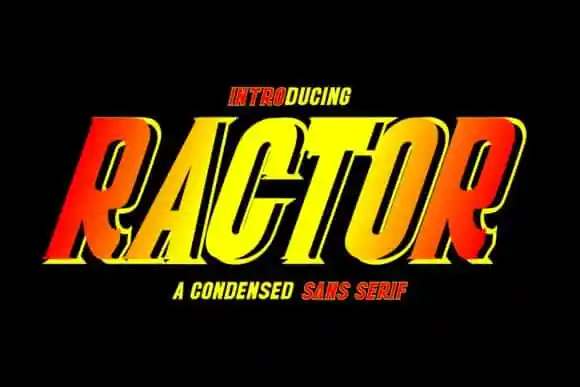
Ractor Display Font – Download Grátis
A Ractor Display Font é uma escolha perfeita para aqueles que procuram um tipo de exibição sem serif vintage e elegante. Conhecida por seu designer Teguh Pranata, a fonte oferece versões Regular e Outline. Ela destaca-se com seus caracteres redondos e prolongados, características que permitem uma aplicação perfeita em logotipos, branding e design de embalagens, entre muitos outros usos visuais. Esta tipografia cuidadosamente criada para fins de exibição é um verdadeiro must-have. Com seu estilo robusto e sofisticado, a Ractor será uma escolha brilhante para seus projetos digitais. Não perca esta oportunidade única de adicionar profundidade ao design de suas aplicações visuais com a Ractor Display Font.